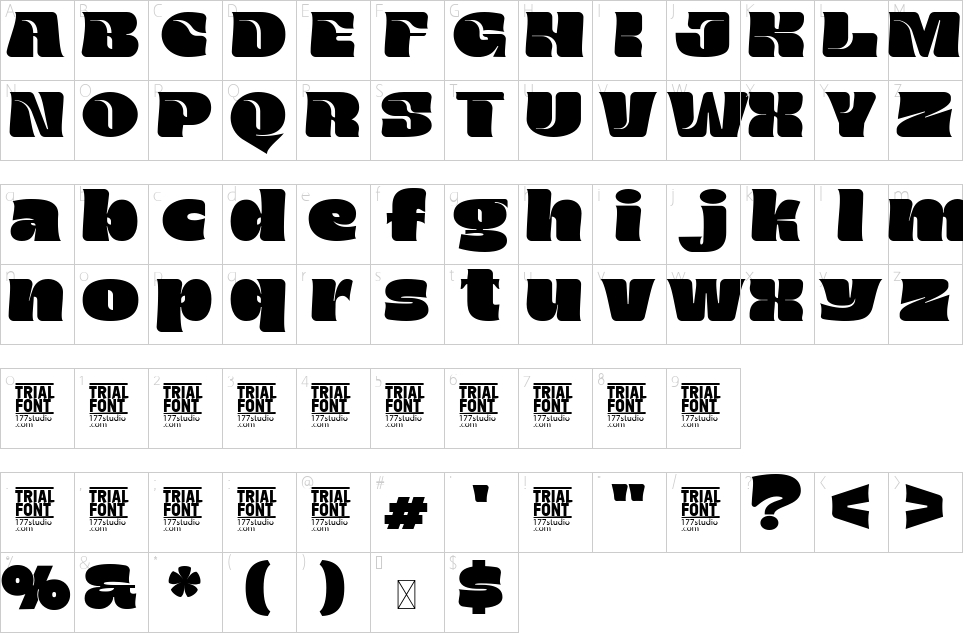
Esta fonte chamada “Medium Unique” foi desenvolvida pela equipe de designers 177studio.com, disponível tanto para sistemas operacionais Windows quanto para Mac. Ela é uma escolha ótima para designers e amantes do design que buscam uma fonte única e moderna. Com seu design único, a “Medium Unique” oferece aos criativos uma opção versátil que combina elegância e originalidade. Esta fonte foi baixada 914 vezes, demonstrando seu valor como uma opção de fonte única e gratuita. Se você está procurando por uma fonte que destaque seu trabalho gráfico, “Medium Unique” é uma fonte que vale a pena explorar.